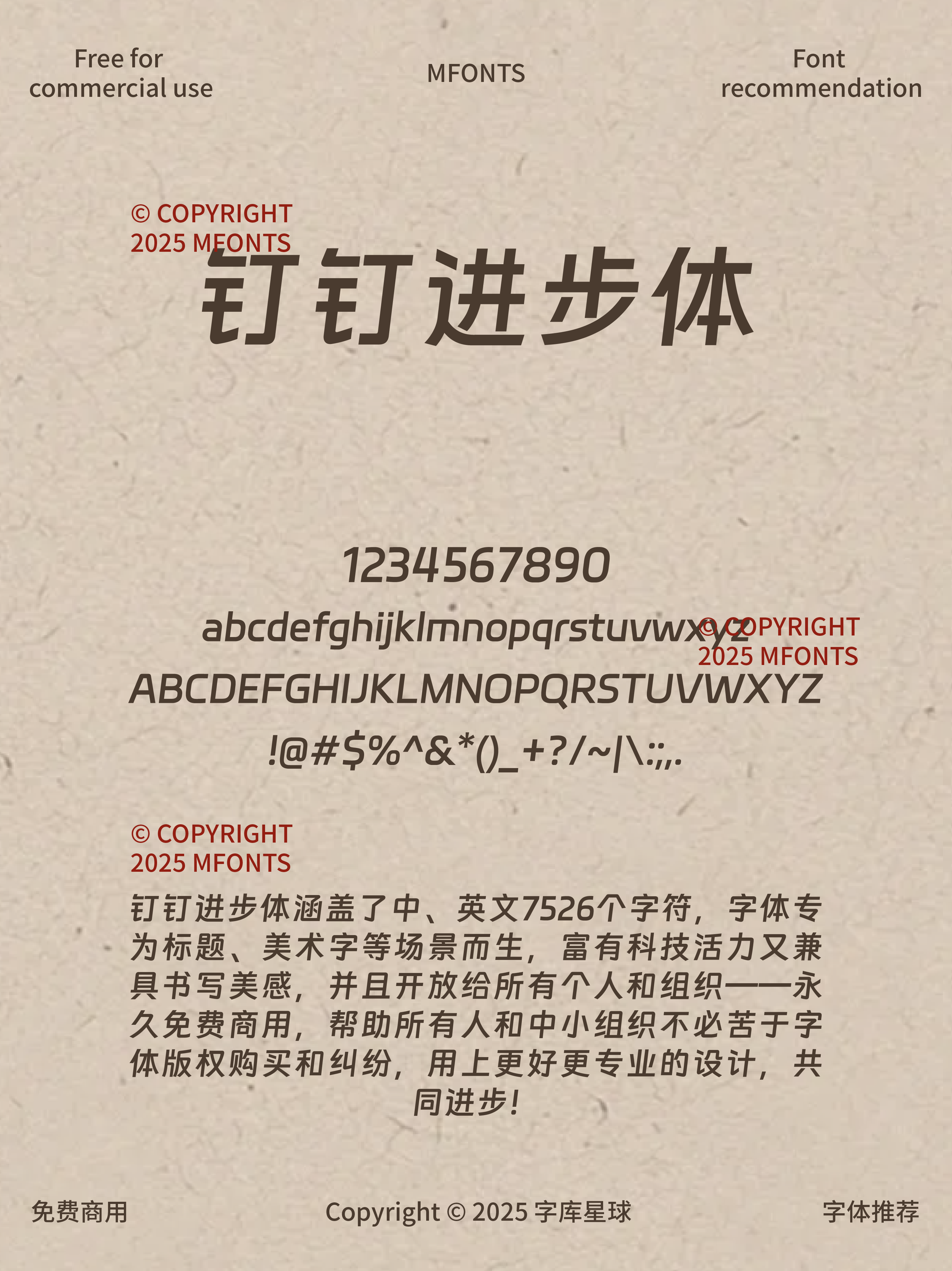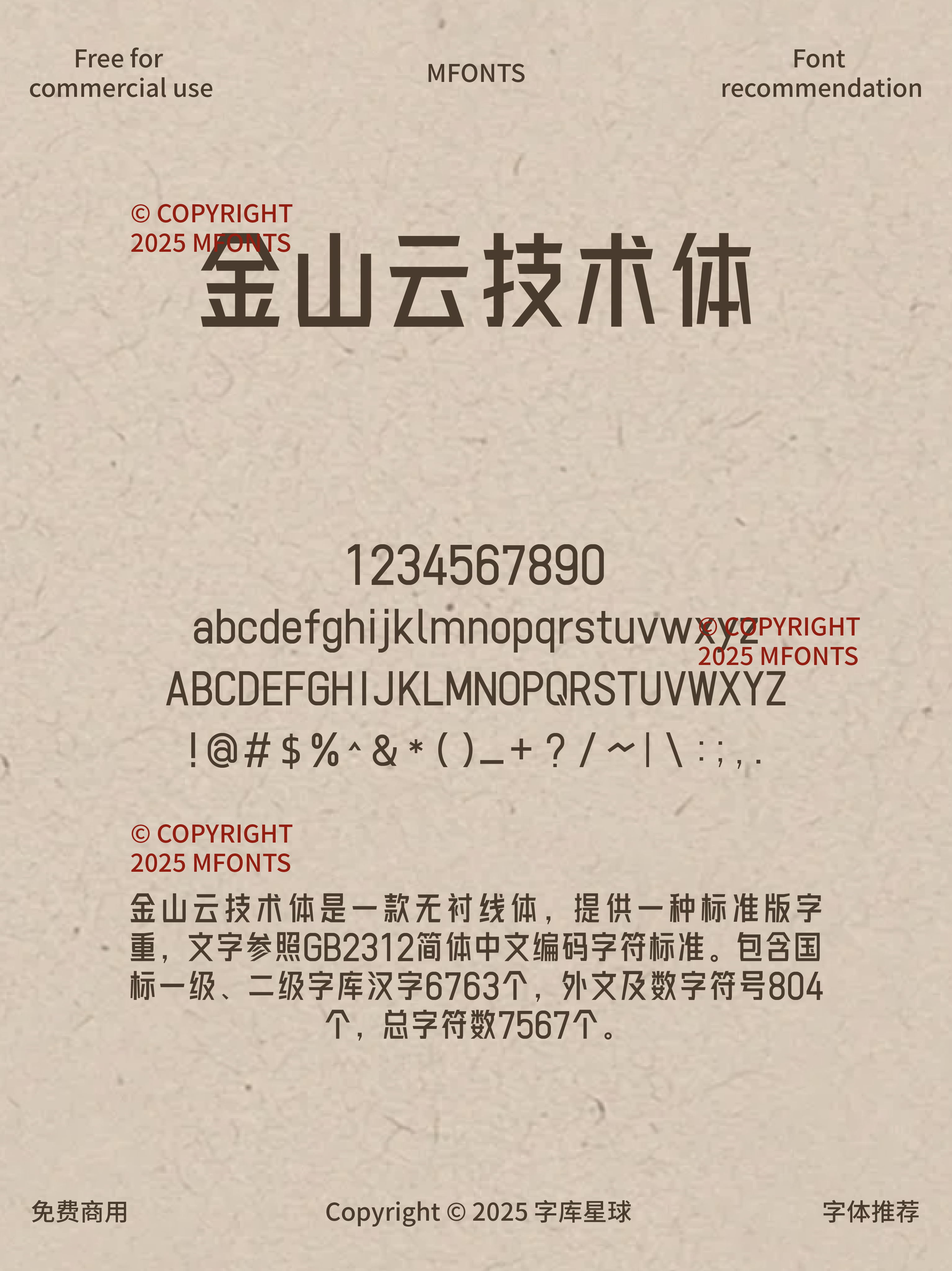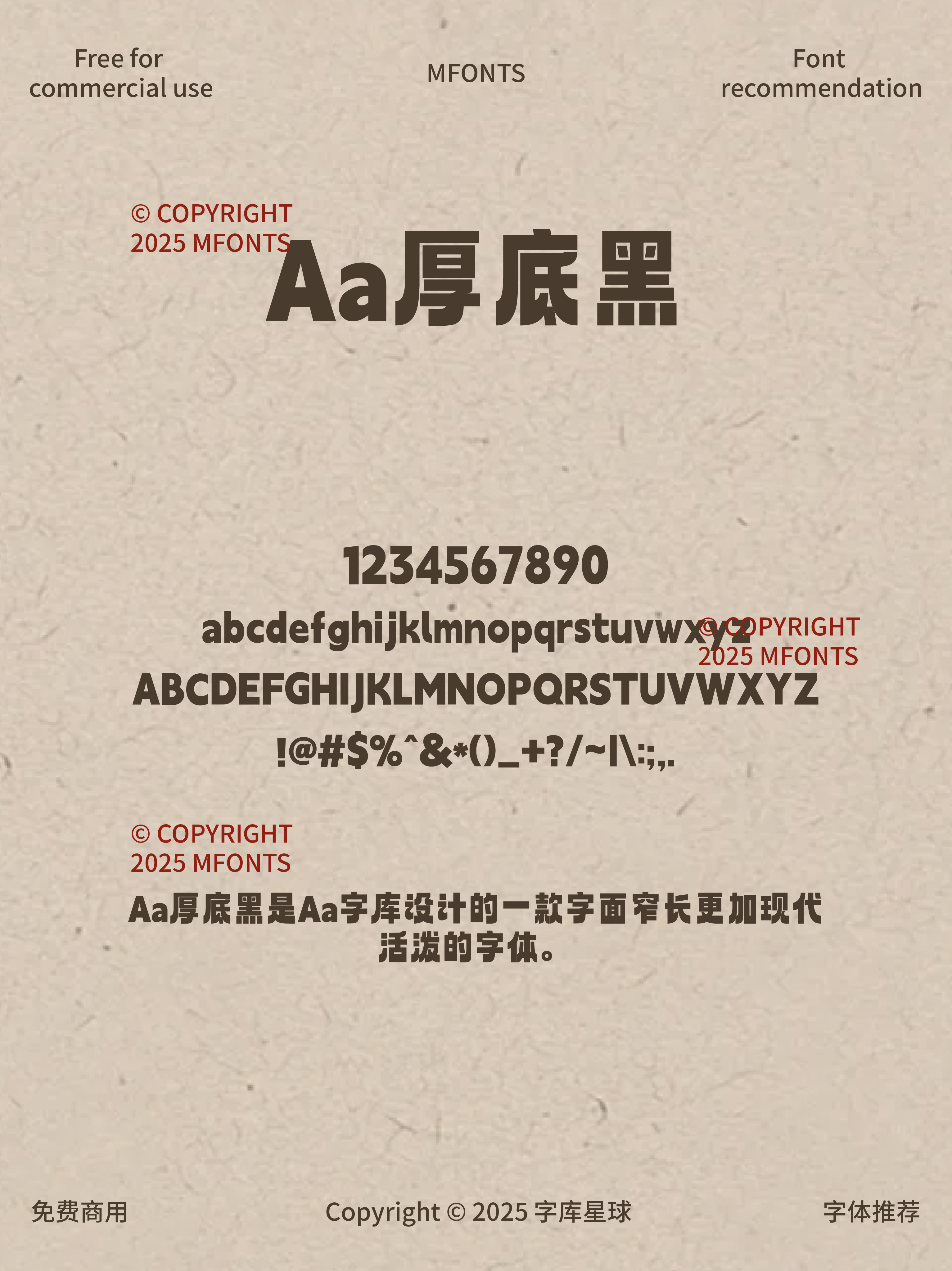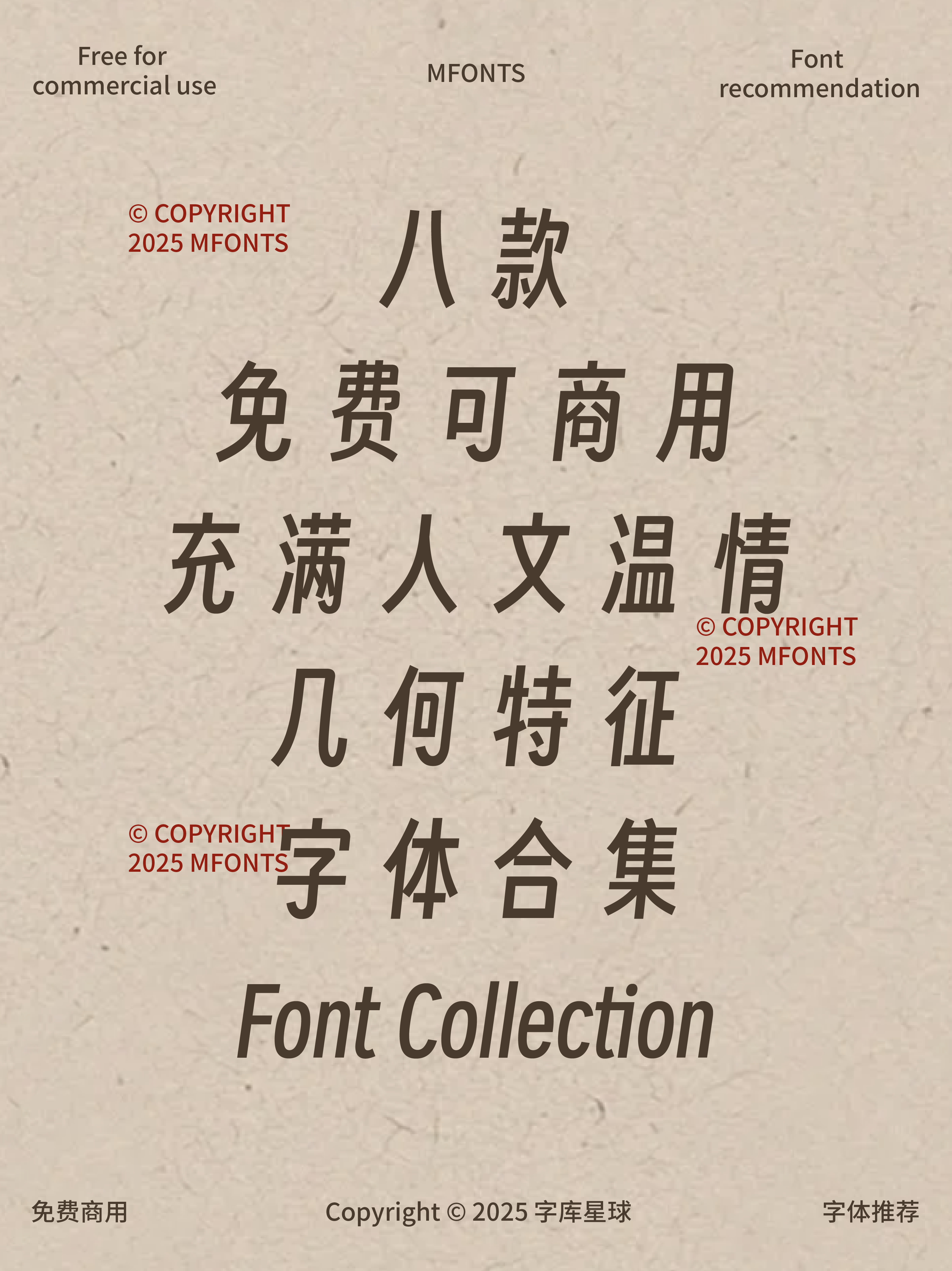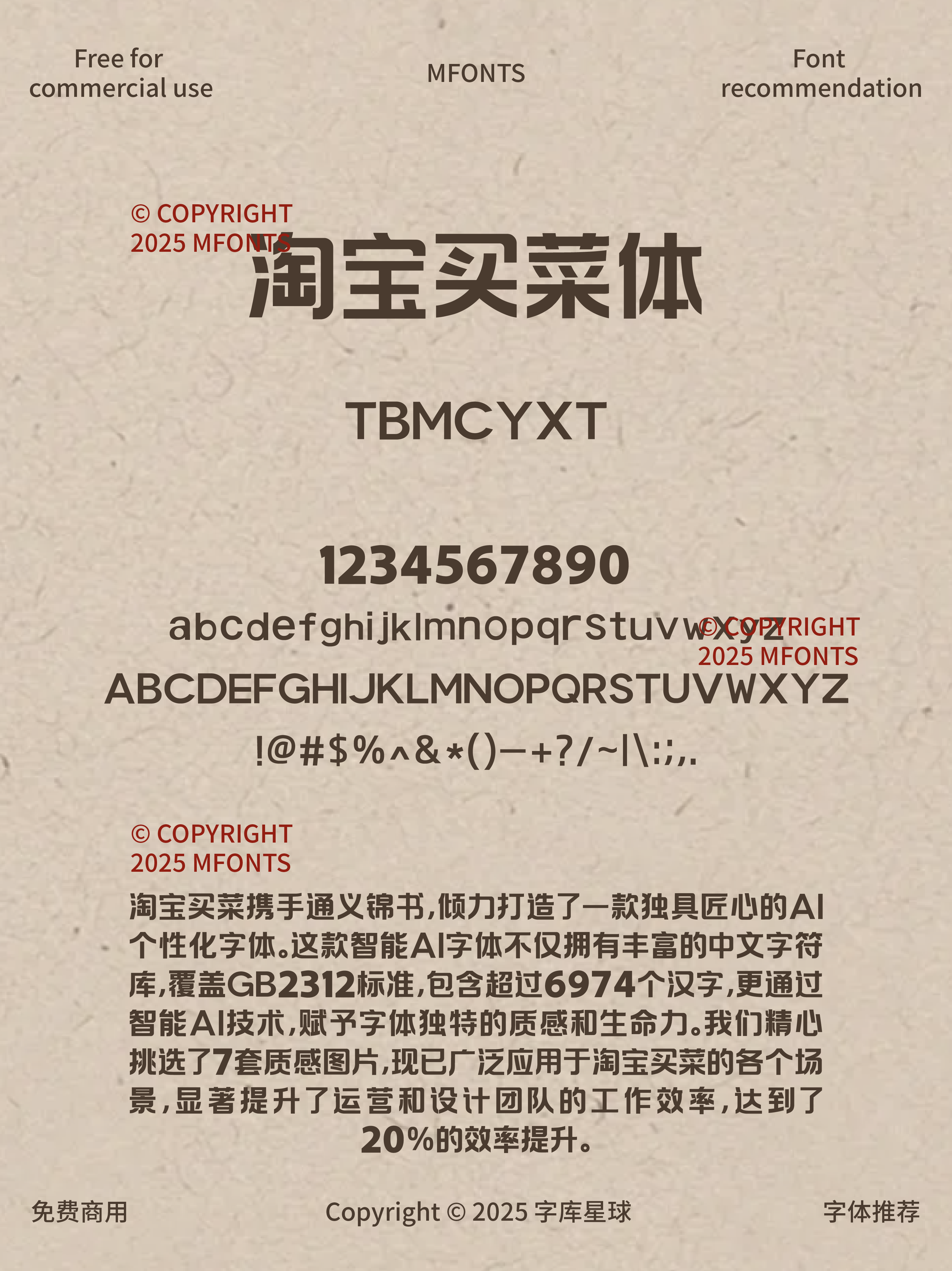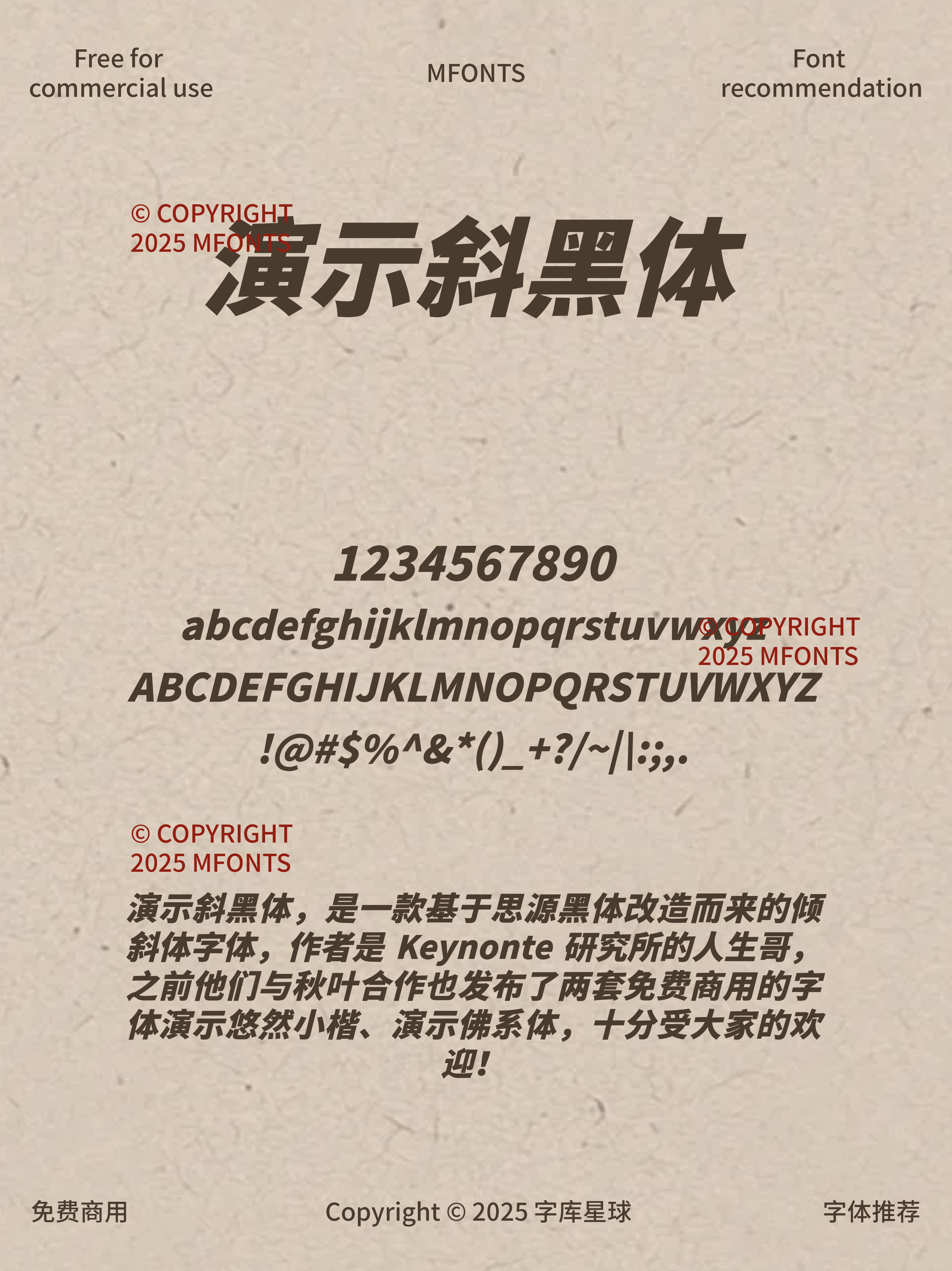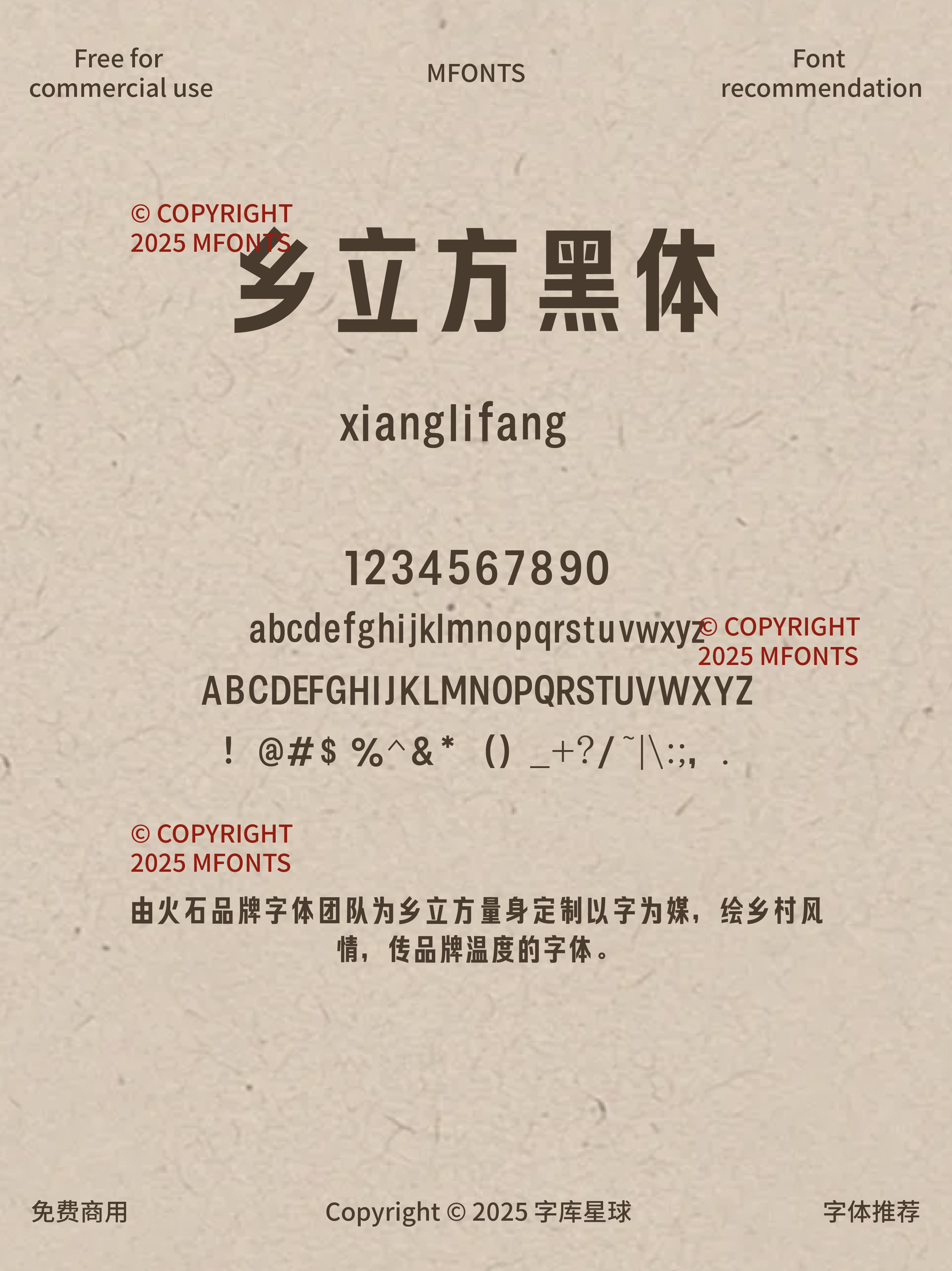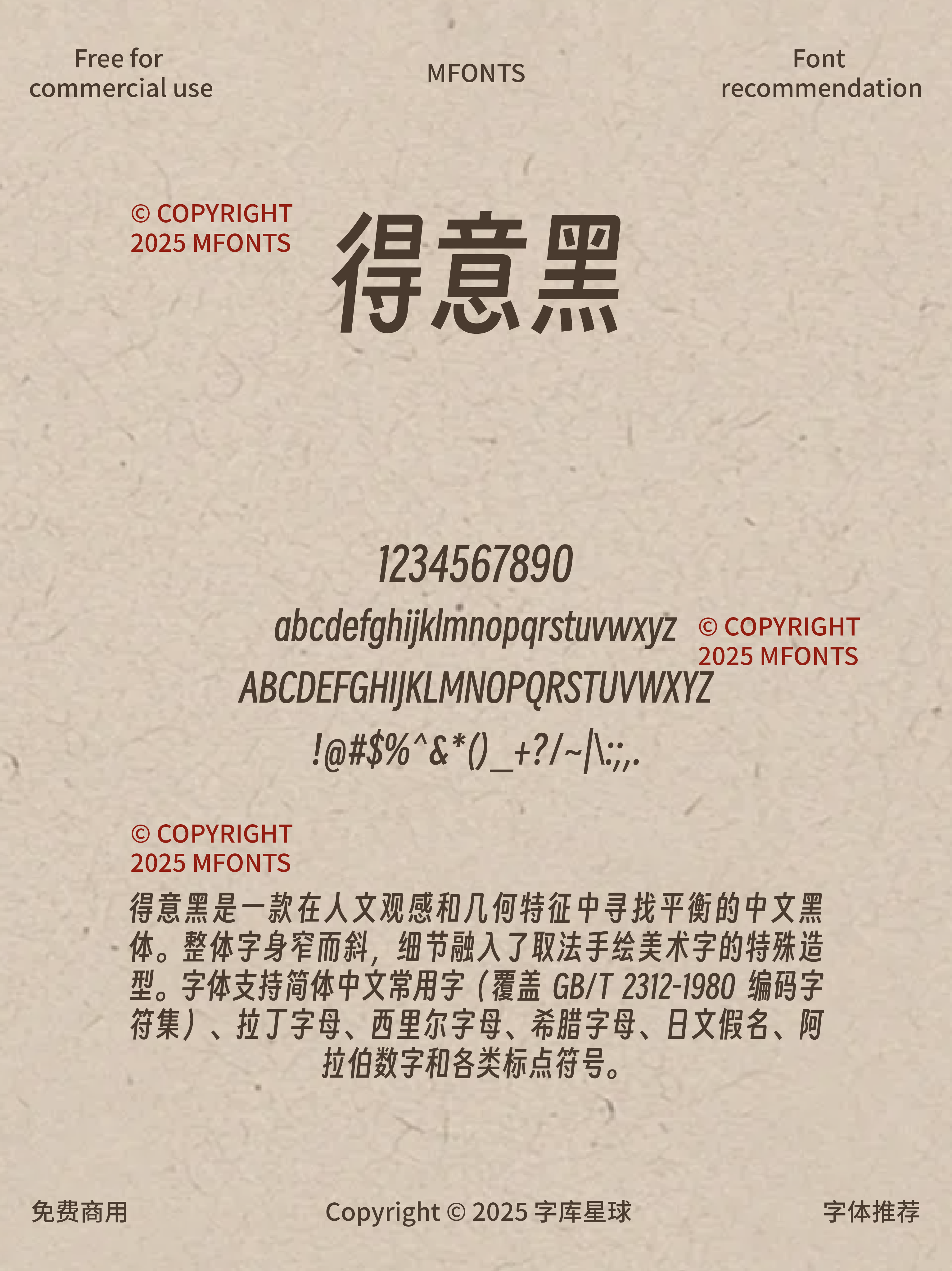
八款免费可商用充满人文温情几何特征字体
今天给大家分享 8 款免费可商用的字体,充满人文温情又带有独特几何特征,设计必备,赶紧码住。
简洁几何线条,笔画粗细均匀,清晰易读,在正文排版、界面设计中表现出色,带来舒适阅读体验。通用性和易用性强,结合几何特征与现代感,电商、广告、品牌形象等场景都能完美适配。